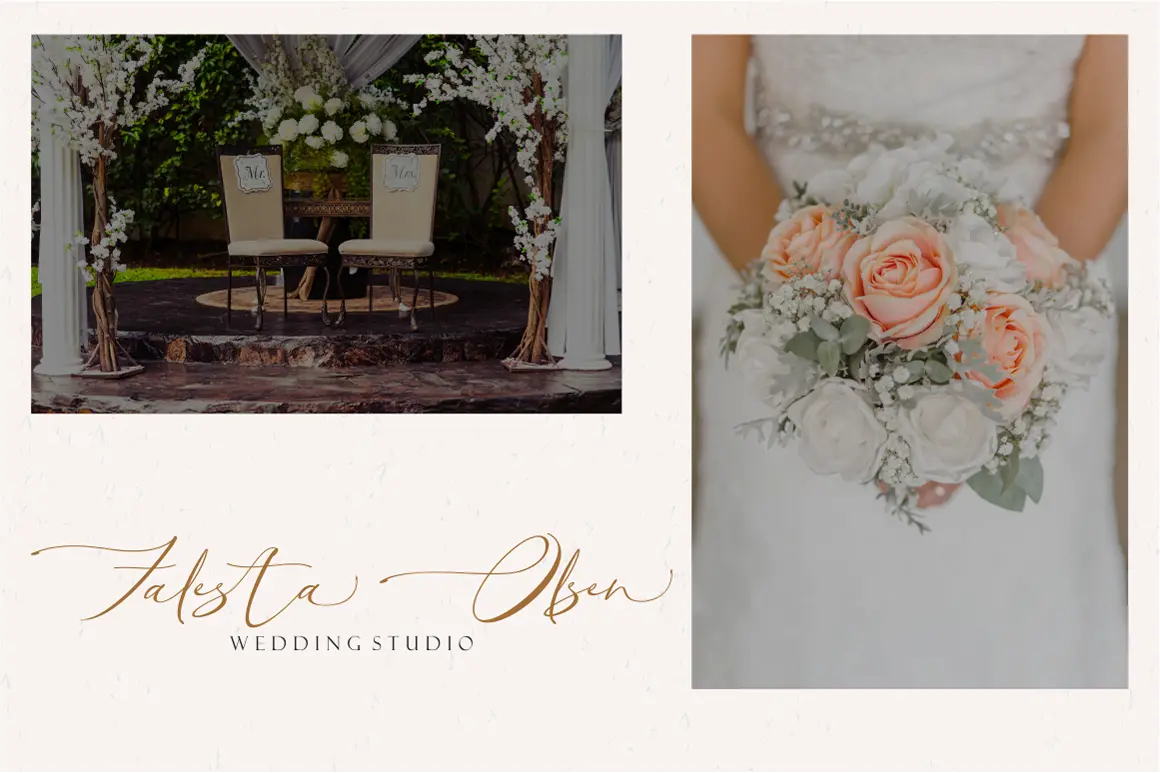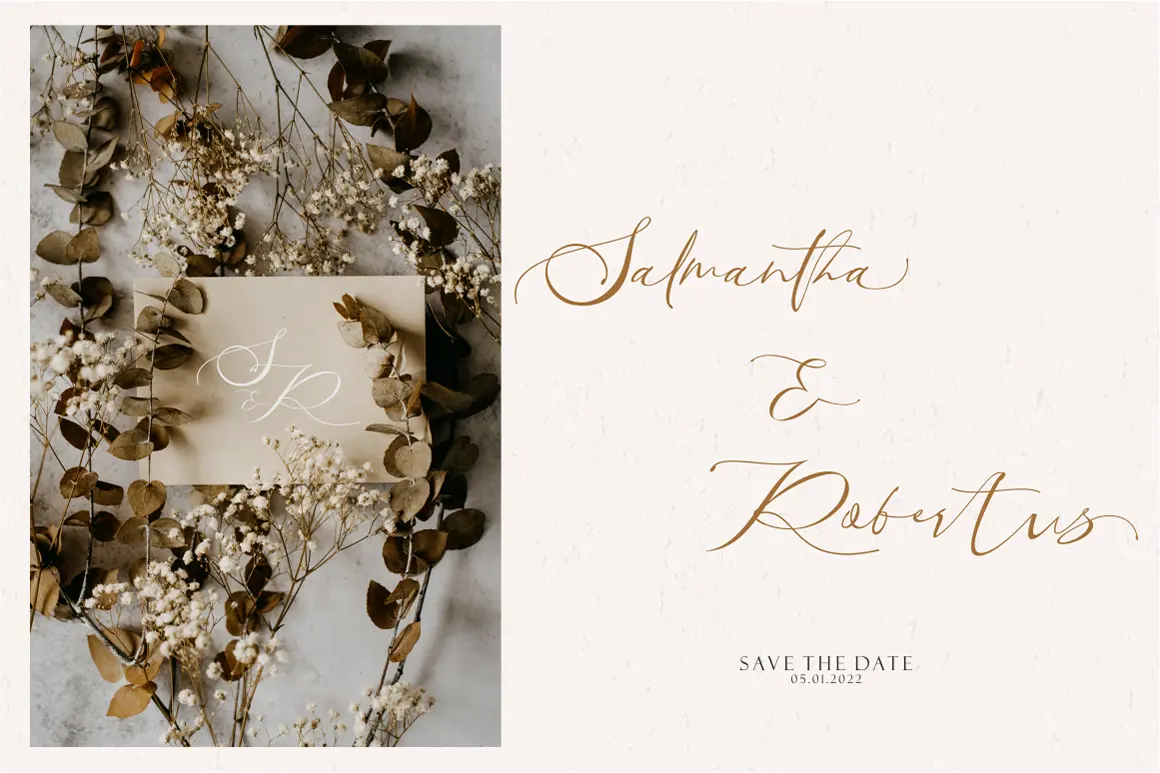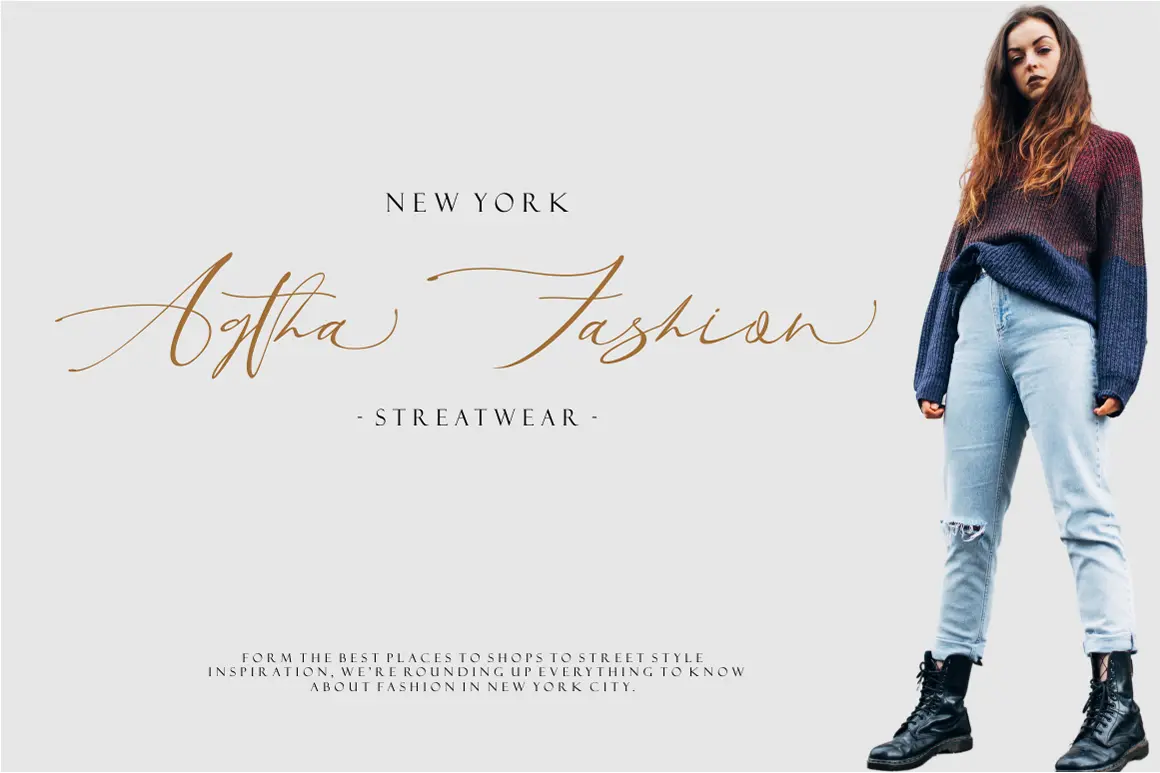
فونت خوشنویسی زیبا و ظریف
فونت Santhania یک فونت اسکریپت زیبا و ظریف است که با الهام از خوشنویسی کلاسیک طراحی شده و فضایی معاصر و حرفهای به نوشتهها میبخشد. این فونت با فرم بینقص و جزئیات دقیق، انتخابی عالی برای پروژههای طراحی لوکس و هنری است. همچنین به دلیل PUA Encoded بودن، دسترسی به تمامی گلیفها و سوئشها بهسادگی امکانپذیر است.
⭐ ویژگیهای محصول
- طراحی اسکریپت ظریف و الهامگرفته از خوشنویسی کلاسیک
- فضای معاصر و حرفهای برای پروژههای مدرن
- دسترسی کامل به گلیفها و سوئشها با PUA Encoding
- مناسب برای لوگو، کارت دعوت، بستهبندی و پروژههای هنری
🎯 موارد استفاده
- طراحی لوگوهای لوکس و هنری
- ساخت کارتهای دعوت و تبریک شیک
- استفاده در بستهبندی محصولات خاص و برندینگ حرفهای
- افزودن به پورتفولیو طراحان گرافیک و تایپوگرافی